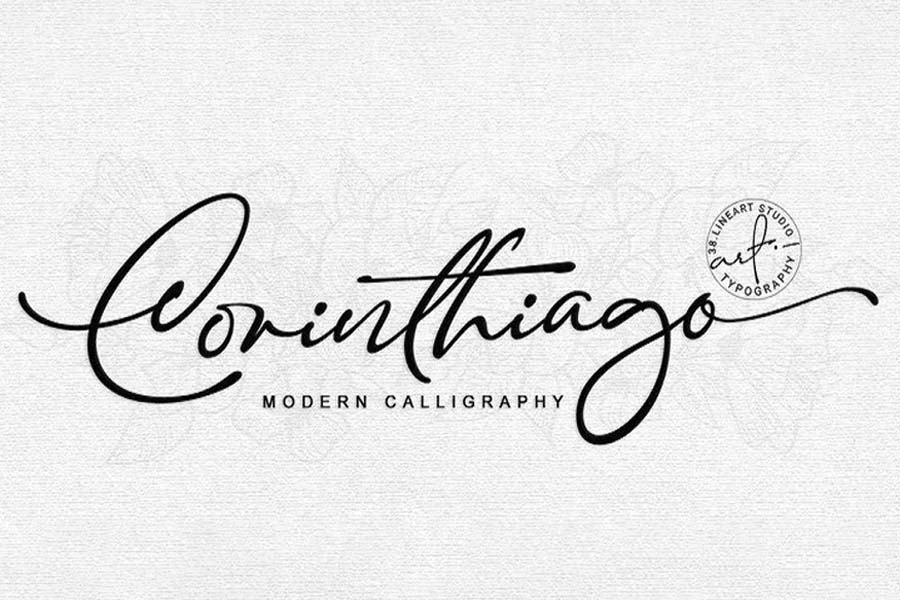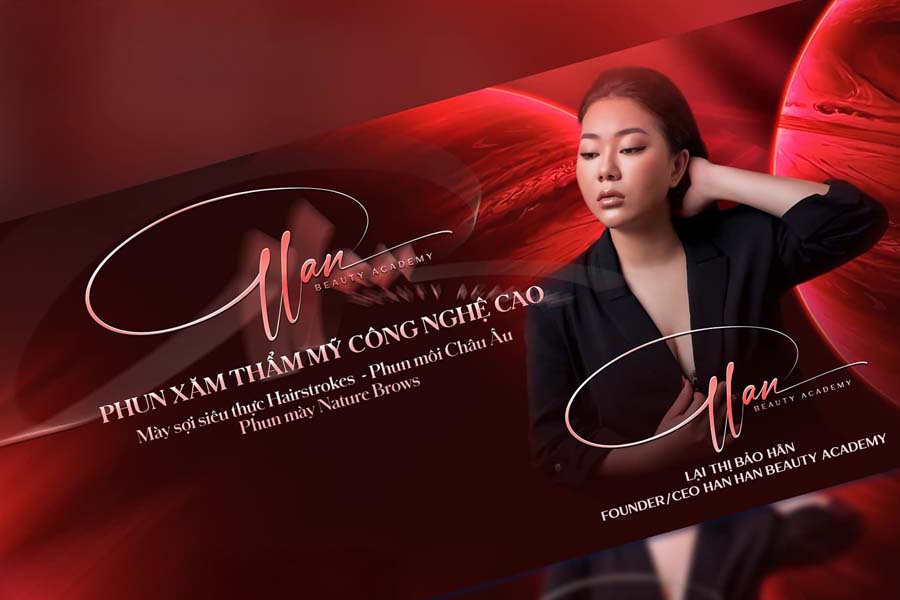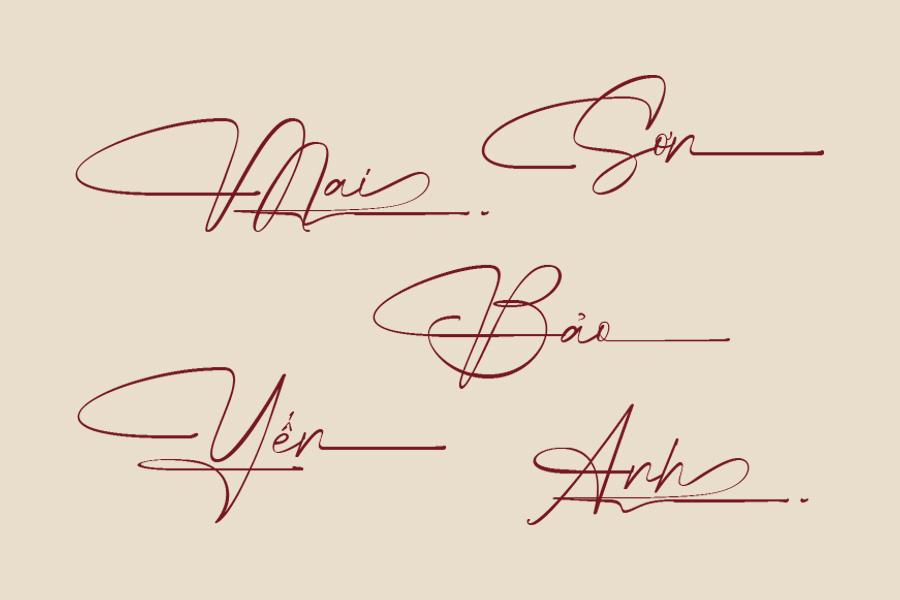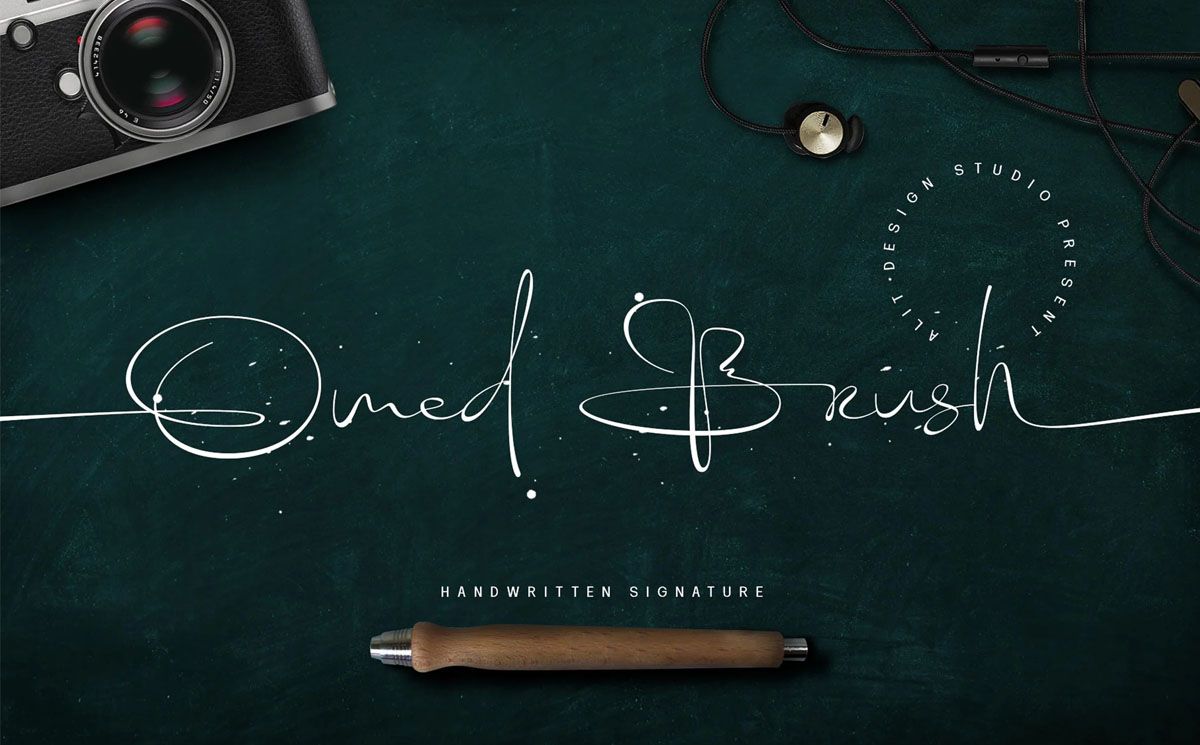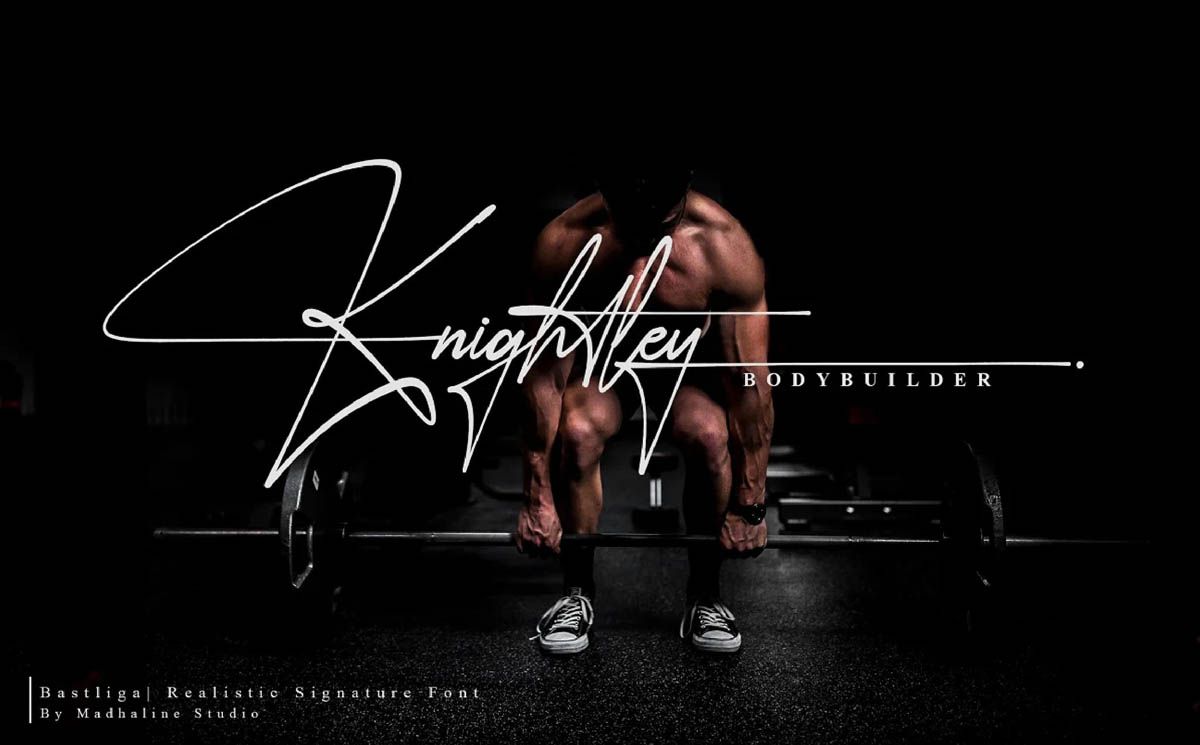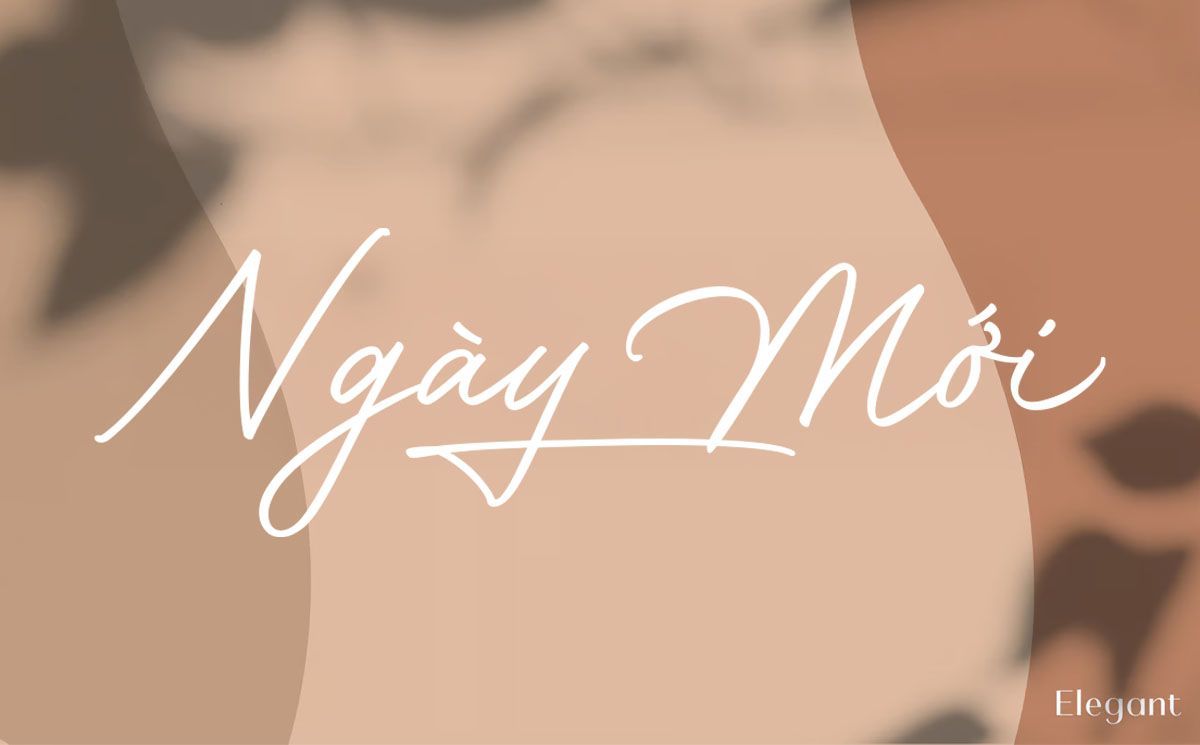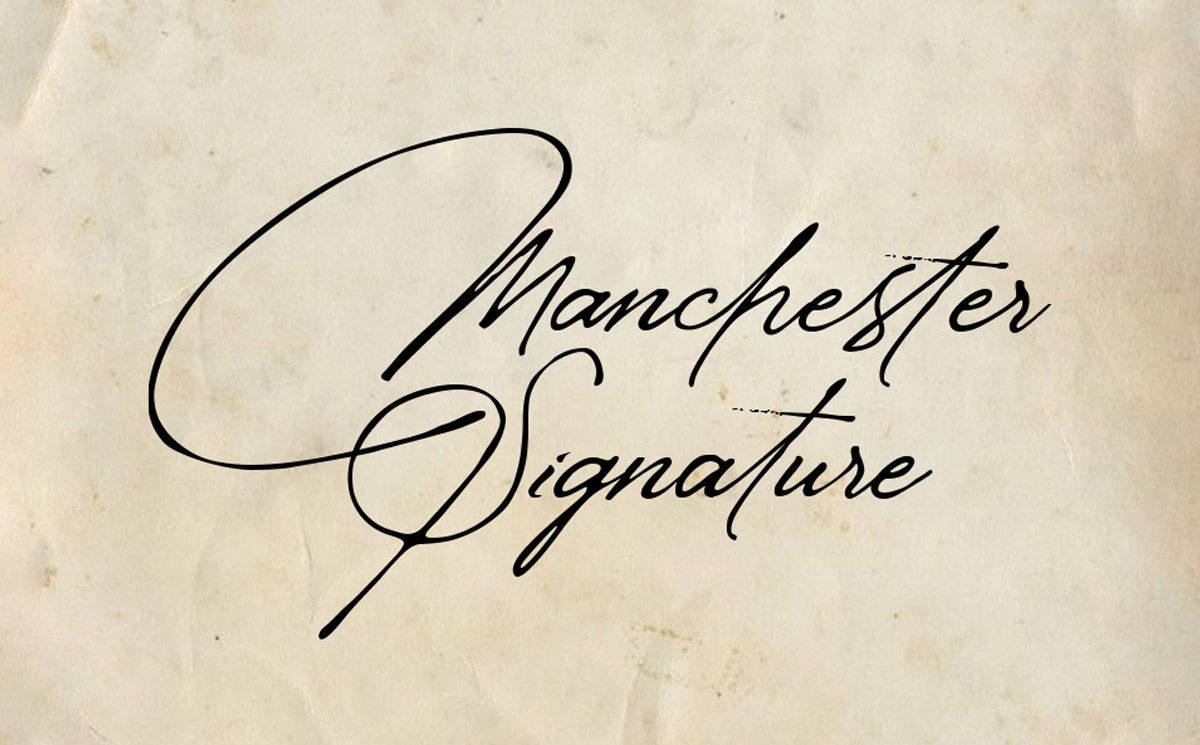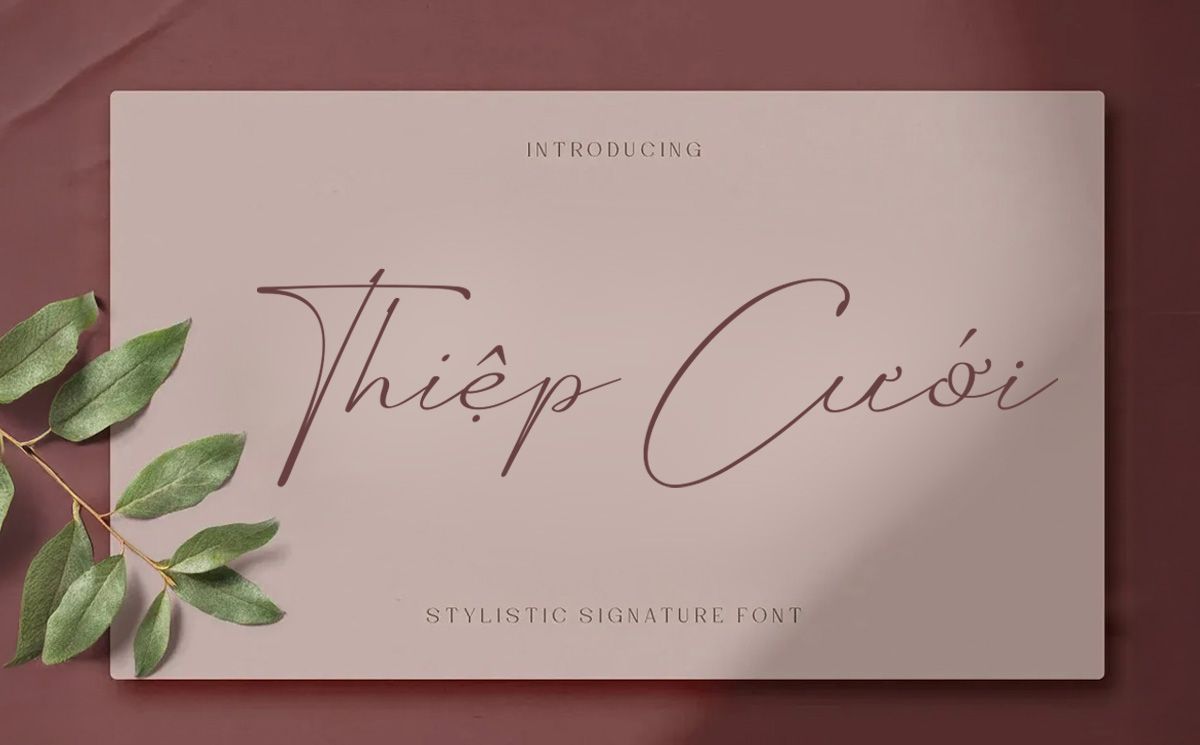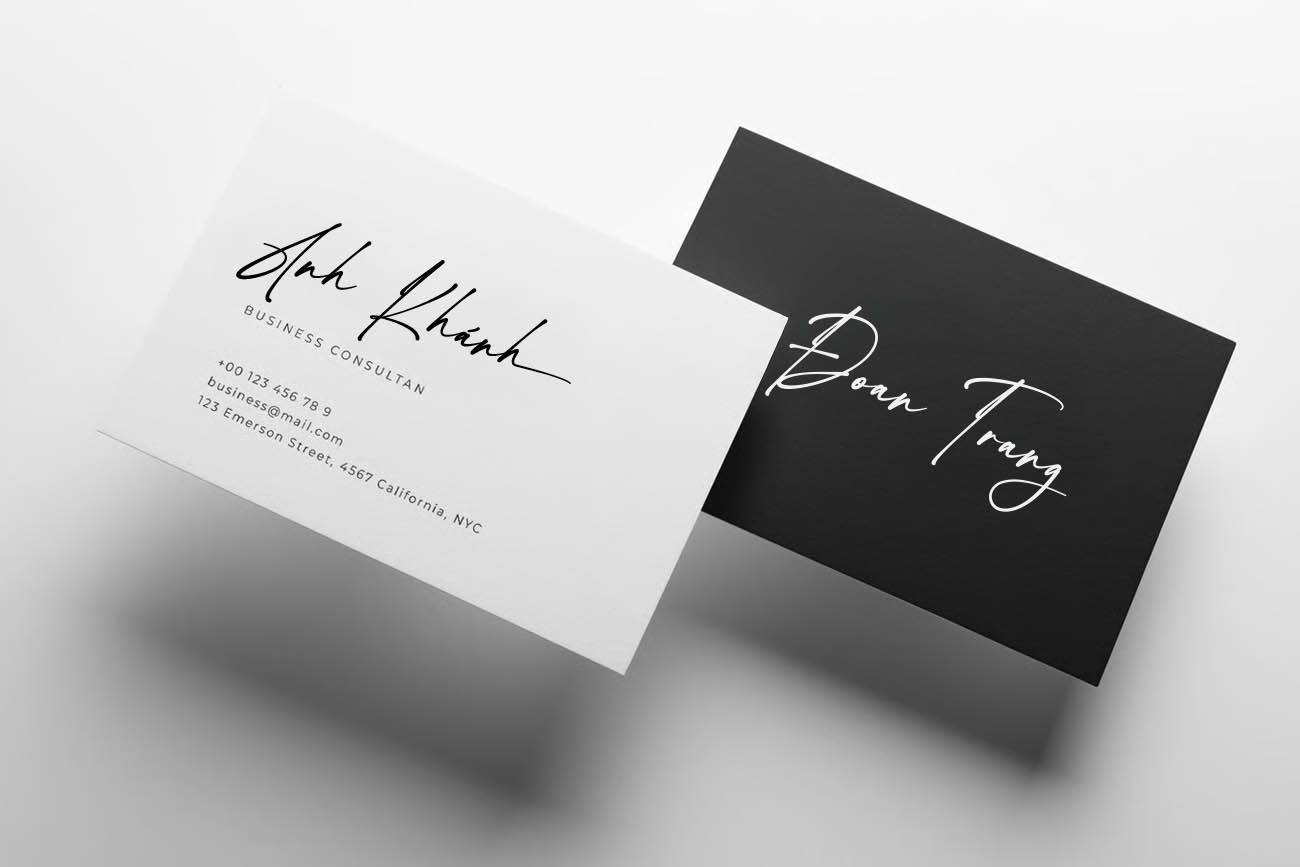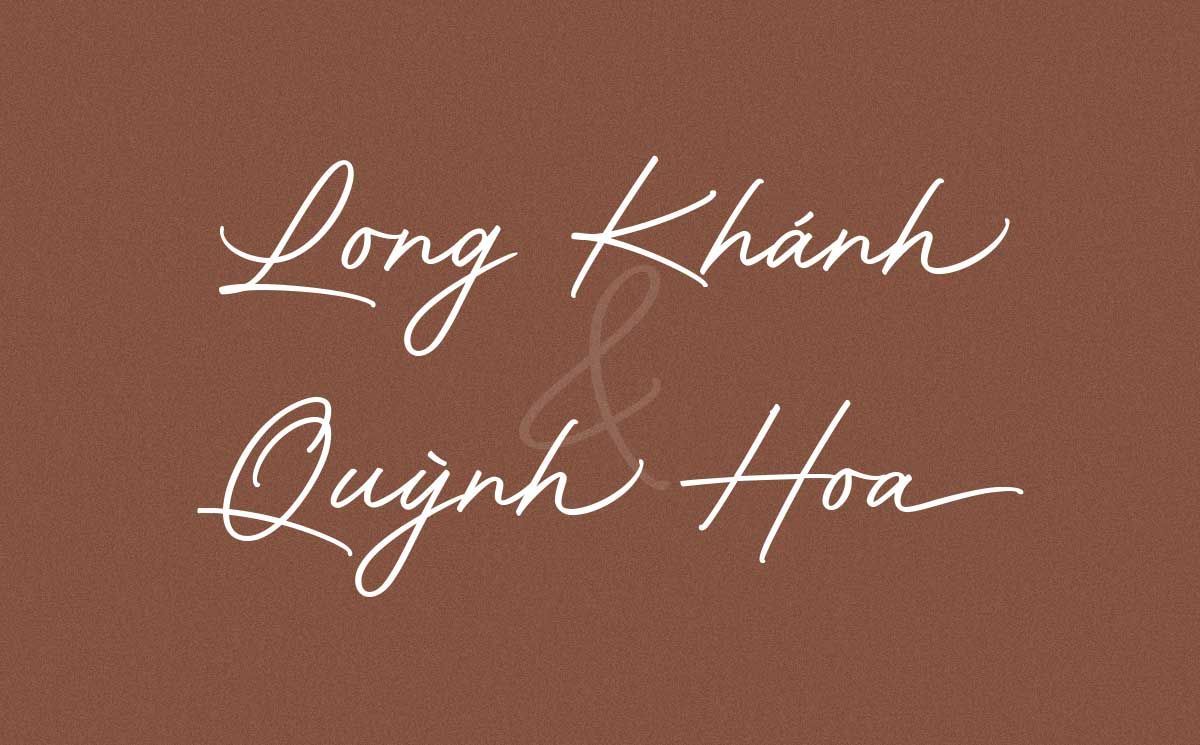
Khám phá 15+ font chữ ký đẹp, đã Việt hóa trọn bộ. Tải sử dụng cho thiết kế logo, thiệp cưới, bao bì, chữ ký cá nhân & thiết kế thương hiệu.
Font Chữ Ký Là Gì? Vì Sao Được Ưa Chuộng Trong Thiết Kế?
Font chữ ký là những kiểu chữ mô phỏng nét viết tay, thường có phong cách uyển chuyển, mềm mại, mang tính cá nhân hóa cao. Đây là lựa chọn lý tưởng để tạo cảm giác thân mật, sang trọng trong các thiết kế như thiệp mời, logo thương hiệu, bao bì sản phẩm, hoặc chữ ký điện tử.
Không giống như các font sans-serif hiện đại, phông chữ ký Việt hóa thường mang theo cảm xúc và bản sắc riêng biệt, giúp thiết kế nổi bật hơn giữa thị trường cạnh tranh.
Đặc Điểm Nổi Bật Của Font  Chữ Ký
Phong Cách Viết Tay Tự Nhiên
Các font chữ ký được thiết kế để mô phỏng chữ viết tay thật – không đều tăm tắp, đường cong mượt mà, giúp mang lại cảm giác cá nhân, gần gũi.
Đa Dạng Phong Cách
Từ mảnh nhẹ, bay bổng đến đậm mạnh, cá tính, font chữ ký có thể đáp ứng nhiều phong cách: thanh lịch, nghệ thuật, thời trang, hoặc sang trọng.
Tính Thẩm Mỹ Cao
Font chữ ký giúp thiết kế trở nên đặc biệt và giàu cảm xúc – yếu tố quan trọng trong thiết kế thương hiệu, wedding, hoặc các sản phẩm mang tính handmade.
Tải Xuống 15 Font Chữ Ký Đẹp Đã Việt Hóa Trọn Bộ
1. TH Manchester Signature – Thanh Lịch, Mềm Mại
TH Manchester Signature là font chữ viết tay phong cách chữ ký thanh lịch, với đường nét uốn lượn mềm mại và tự nhiên. Thiết kế mô phỏng nét bút tay uyển chuyển giúp font trở nên lý tưởng cho các dự án cá nhân hóa như logo, thiệp cưới, danh thiếp hoặc bao bì cao cấp.
2. TH Wellyon – Bay Bổng, Tự Nhiên
TH Wellyon là font chữ viết tay mang phong cách hiện đại và bay bổng, với các nét bút mềm mại, tự nhiên như được viết bằng tay thật. Font tạo cảm giác nhẹ nhàng, tinh tế nhưng vẫn giữ được sự rõ ràng và dễ đọc. Các ký tự được chăm chút tỉ mỉ, tạo nên vẻ đẹp thanh thoát và đầy cảm xúc.
3. TH Omaha Beach – Mạnh Mẽ, Cá Tính
TH Omaha Beach là font chữ ký hiện đại, phóng khoáng với nét bút to, dày và uốn lượn mạnh mẽ. Phù hợp cho tiêu đề, poster, logo thời trang và thiết kế cá tính. Hỗ trợ nhiều ký tự thay thế, linh hoạt trong sáng tạo.
4. TH Nice Memory – Lãng Mạn, Dễ Dùng
TH Nice Memory là font chữ ký mang phong cách viết tay hoài niệm, với các nét dài, mảnh và uyển chuyển như những dòng thư tay xưa. Font tạo cảm giác lãng mạn, sâu lắng và rất phù hợp cho các thiết kế mang tính cá nhân như logo thương hiệu, thiệp cưới, hình ảnh kỷ niệm hay bìa sách nghệ thuật cần truyền tải cảm xúc một cách tinh tế và chân thực.
5. TH Frenchasette – Nhẹ Nhàng, Đầy Cảm Xúc
TH Frenchasette là font chữ ký viết tay mang phong cách nhẹ nhàng, uyển chuyển và tinh tế. Với các nét chữ thanh mảnh, mềm mại và đầy cảm xúc, font tạo cảm giác lãng mạn, rất phù hợp với thiết kế thiệp mời, logo cá nhân, hoặc các ấn phẩm mang tính nghệ thuật và thời trang. Thiết kế của font giúp tăng tính cá nhân hóa mà vẫn giữ được sự hiện đại và chuyên nghiệp.
6. TH Corinthiago – Cổ Điển, Mảnh Mai
TH Corinthiago là một font chữ ký hiện đại pha nét hoài cổ, được thiết kế bởi 38.lineart và Việt hóa bởi Phạm Sơn. Font có kiểu dáng mềm mại, đường nét uyển chuyển như chữ viết tay thực, mang đến cảm giác gần gũi và chân thành. Đặc biệt phù hợp cho thiệp cưới, logo, bìa sách, hoặc các thiết kế mang tính cá nhân.
7. TH Omed Brush – Phá Cách, Mạnh Mẽ
TH Omed Brush là font chữ viết tay nghệ thuật với các đường nét dài, mảnh và phá cách, tạo nên phong cách đầy cá tính và tự do. Điểm nhấn của font nằm ở những vòng lượn sáng tạo, mang lại cảm giác như một bức vẽ tay đầy ngẫu hứng. Rất lý tưởng cho các thiết kế mang dấu ấn cá nhân như bìa sách, ảnh nghệ thuật hay thương hiệu thời trang. Font được thiết kế bởi Alitdesign và Việt hóa bởi Phạm Sơn.
8. TH Milyah – Thanh Thoát, Tinh Tế
TH Milyah là một font chữ ký thanh mảnh, nhẹ nhàng với phong cách viết tay uyển chuyển và duyên dáng. Các đường nét cong mềm kết hợp với đuôi chữ kéo dài tạo cảm giác tự nhiên, tinh tế. Font đặc biệt phù hợp để thiết kế chữ tên cá nhân, thiệp cưới, hoặc logo spa, mỹ phẩm. Font được thiết kế bởi Alit Design và Việt hóa bởi Phạm Sơn.
Kết Luận
Với top 15 font chữ ký đẹp và đã Việt hóa trên, bạn sẽ có trong tay những công cụ tuyệt vời để nâng tầm thiết kế logo, thiệp mời, bao bì sản phẩm hay chữ ký cá nhân. Đừng chỉ dùng những font mặc định – hãy để mỗi nét chữ của bạn thể hiện một dấu ấn riêng biệt!